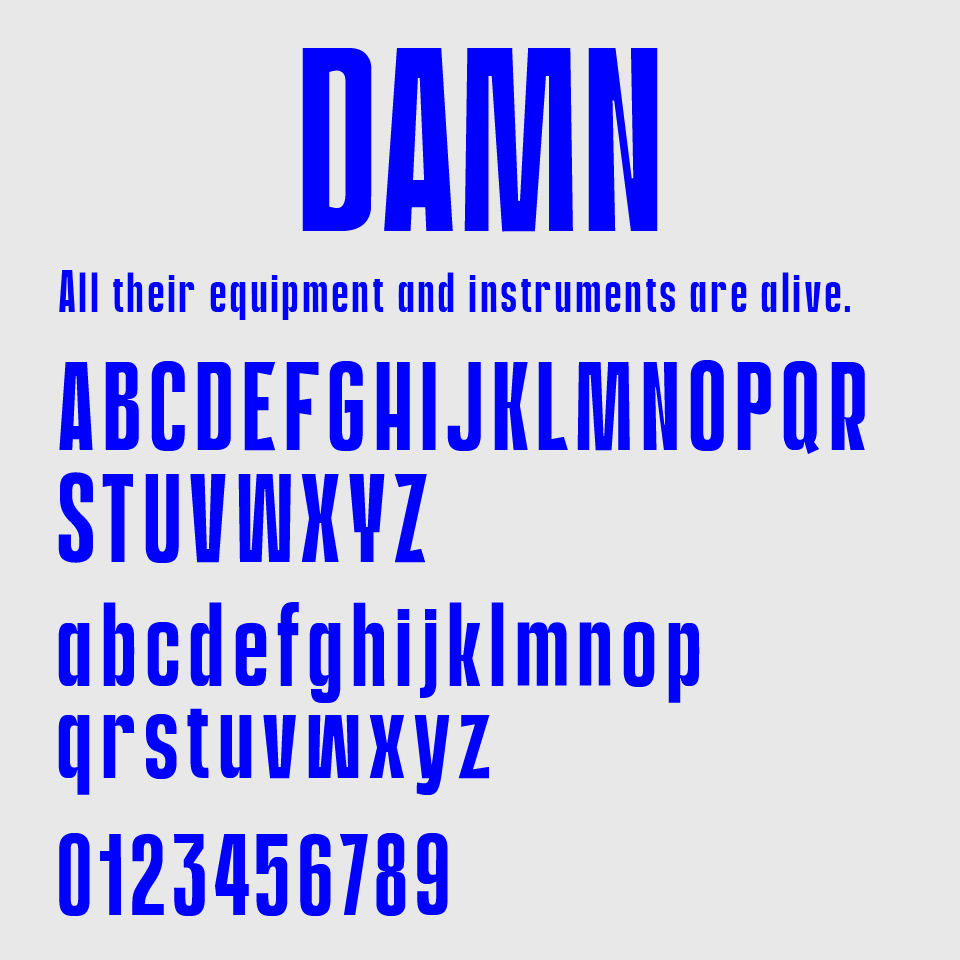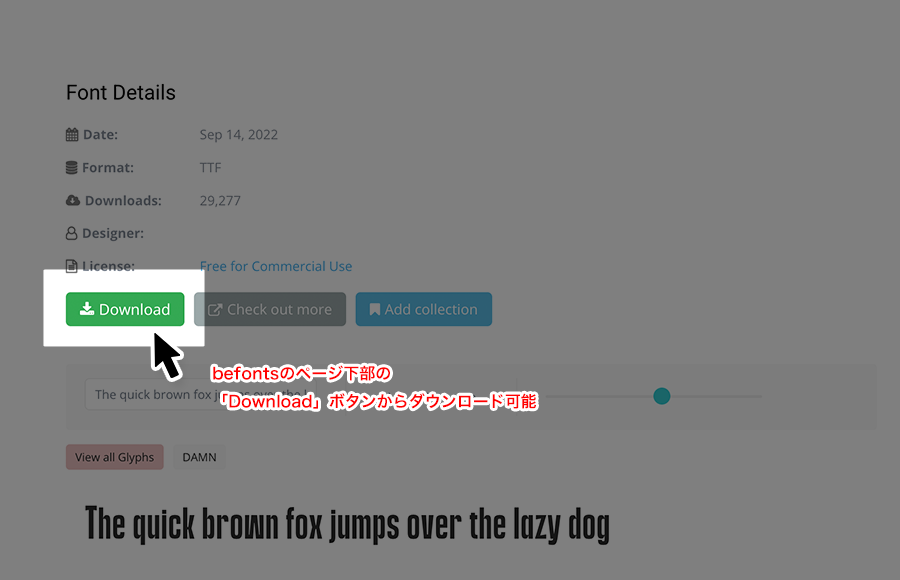
Damnフォントは、縦にぐっと伸びたインパクトのあるサンセリフ体フォントです。
ウルトラコンデンスなスタイルと直線的な輪郭が特徴で、視線を強く引きつけるデザインです。大文字中心の設計で、並べるだけでポスターのような雰囲気が生まれます。シンプルながらちょっとした部分で、凹みが入っていたり、尖った個性を表現できるフォントです。
このフォントは、力強く無駄のないデザインを好む場面にぴったりです。ストリート系のカルチャーやエレクトロニックなテーマ、音楽イベントなどのタイトルロゴにもぴったりです